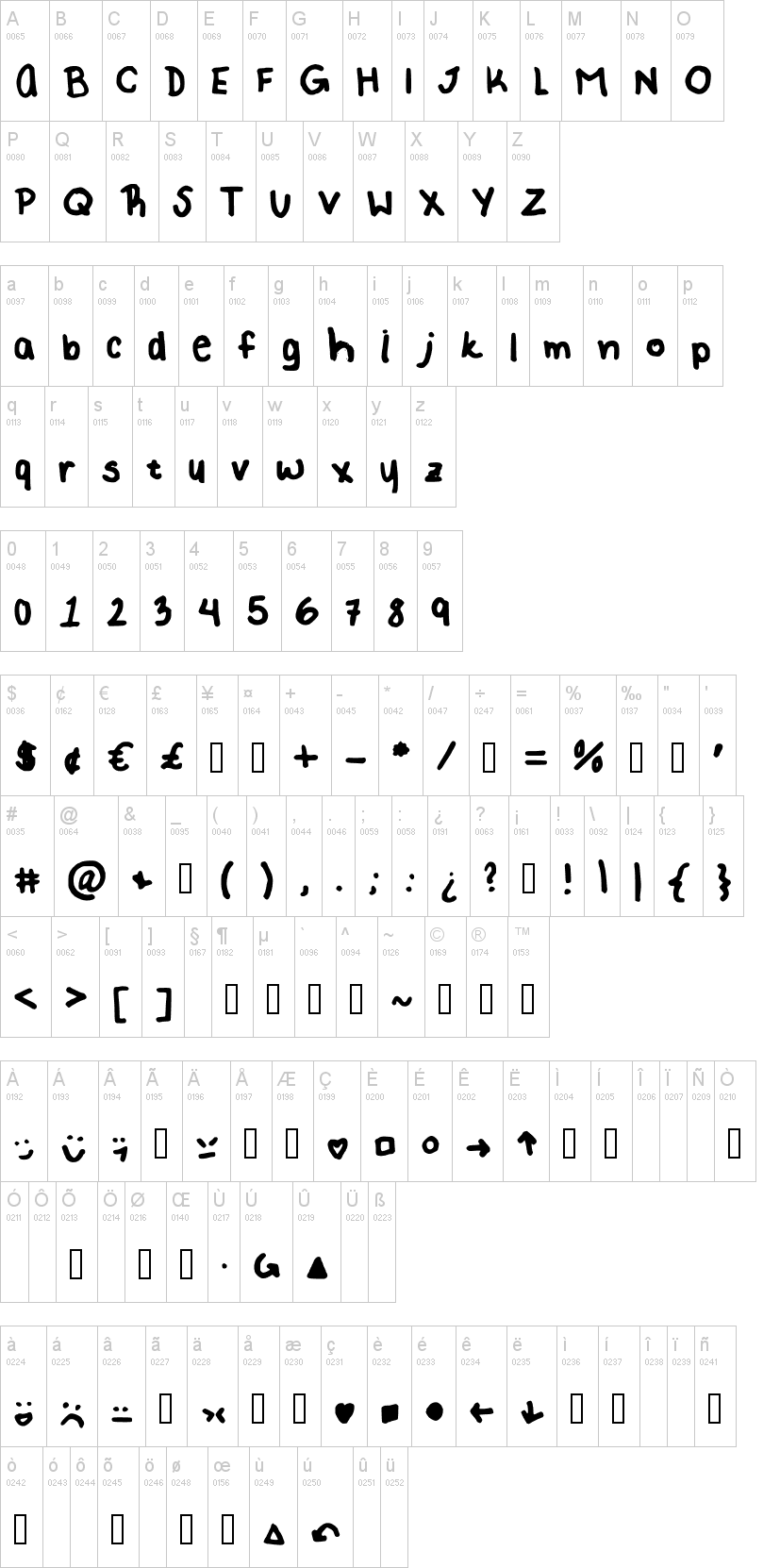
Rachel Kate是一款由Tugcu Design Co.设计的新款手写体字体,它具有温暖的质感,细腻的笔触,而且还有许多可爱的装饰性元素。它可以用于各种应用,如印刷、网页设计、标志、海报等,为您的文字添加一种温暖的感觉。内容介绍
Rachel Kate是一款非常不错的手写艺术字体,具有很好的视觉感,适合于文化类的宣传设计、商业类品牌的广告和产品包装设计以及个性化文字排版等较多场景。